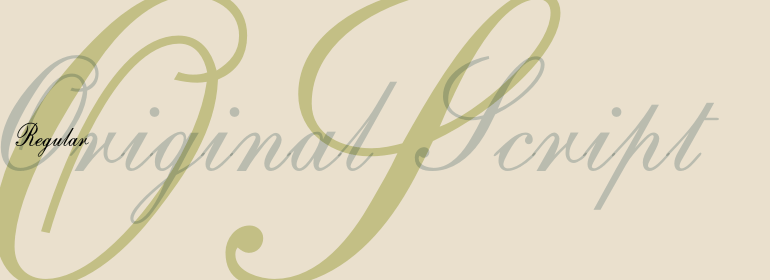
Original Script™
Original Script™,这款字体结构工整、笔画清晰,兼顾美观与易读性,适用于标题、正文、海报、包装、LOGO 等多种场景。字形优雅稳定,风格百搭耐看,适配日常排版与创意设计,让文字呈现更舒适、更具质感。Original Script™一笔一画,皆是细节,以均衡的比例、流畅的线条打造舒适视觉体验,字形端正大气,风格简约现代。无论是商业设计、品牌宣传还是日常排版,都能轻松驾驭,让文字更有格调与力量。Original Script™字体下载。
这一手写家族可用于广告、邀请函、贺卡以及任何需要正式手绘或雕刻外观的地方。Original Script优美的连笔字母表是基于书法笔迹。Original Script字体用于婚礼与正式场合的邀请函,以及个人信笺比较稳妥。
This script collection is used in advertising, invitations, greeting cards, and wherever a formal hand-lettered or engraving look is desired. Original Script has an elegant connecting alphabet based on formal handwriting. The Original Script font is a safe choice for invitations to weddings and formal occasions, and personal stationery.